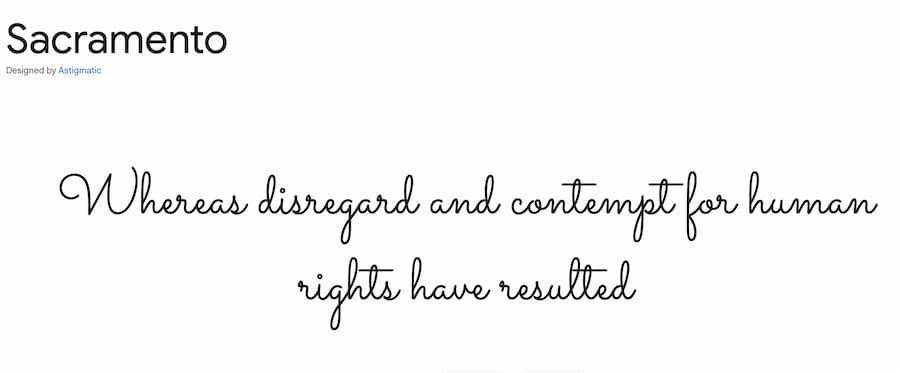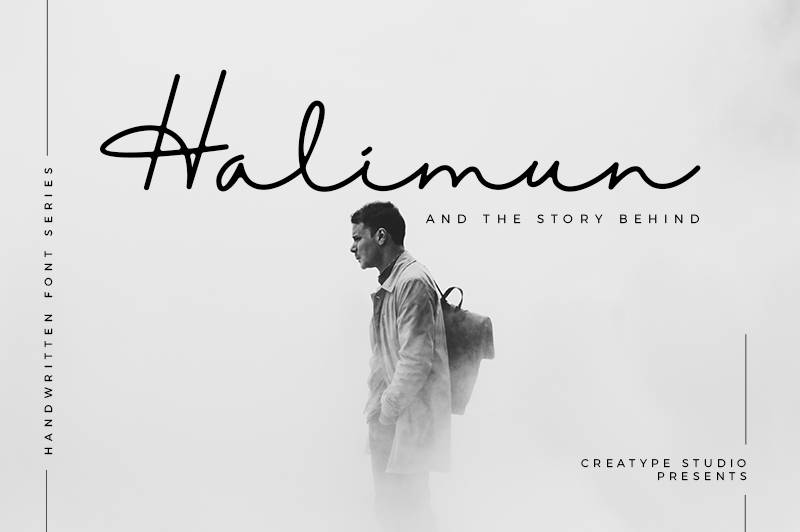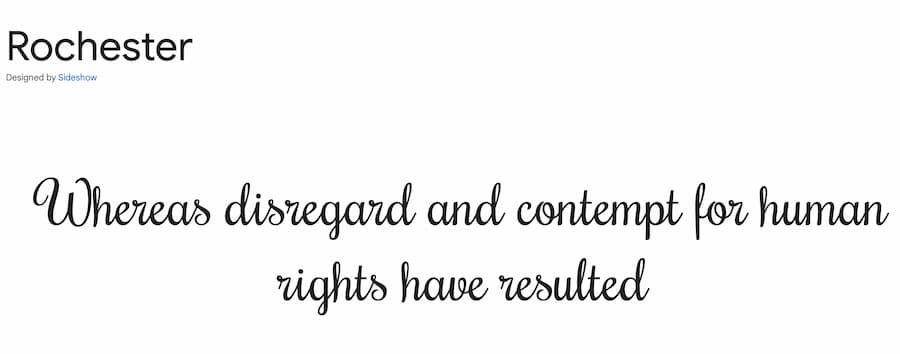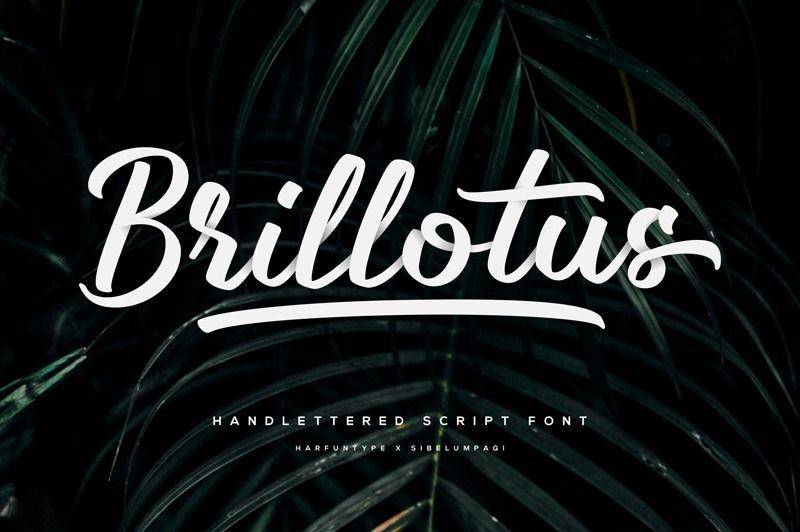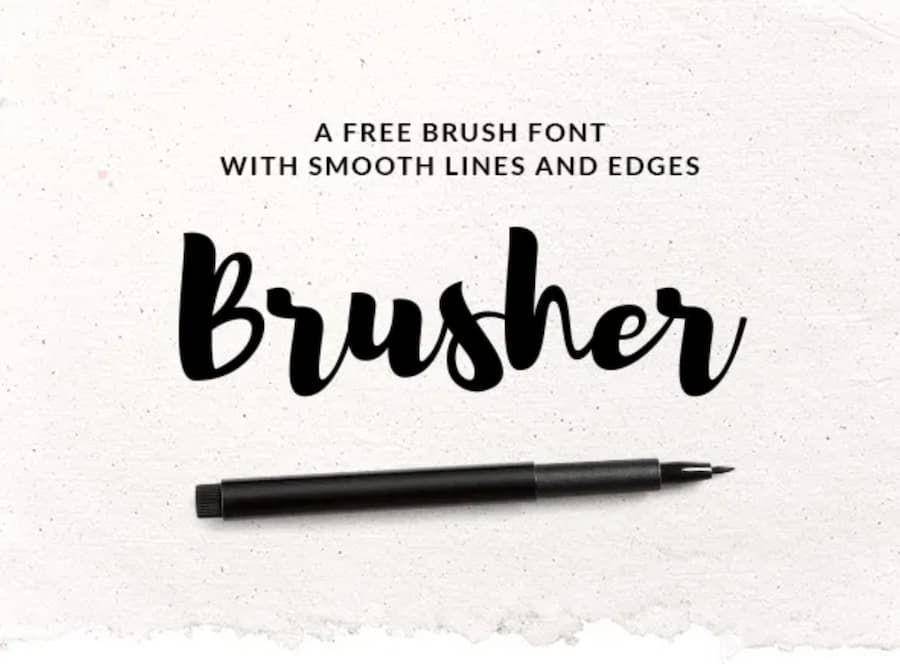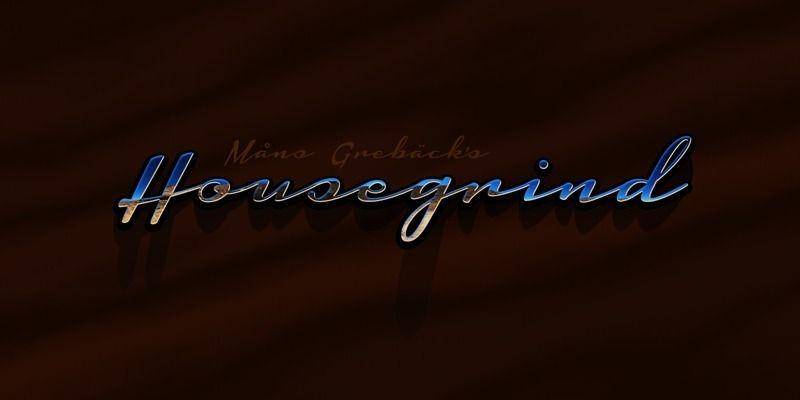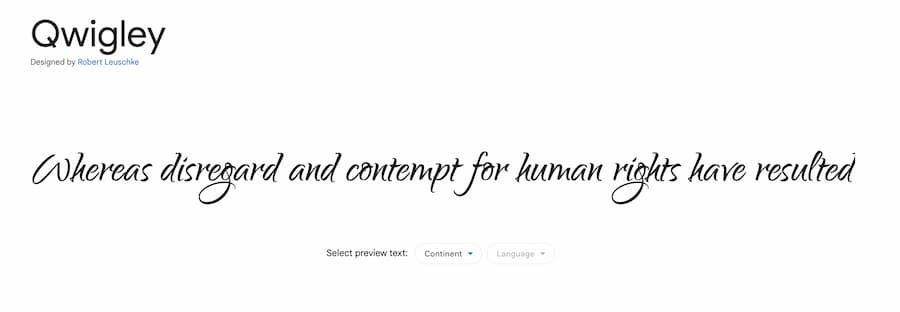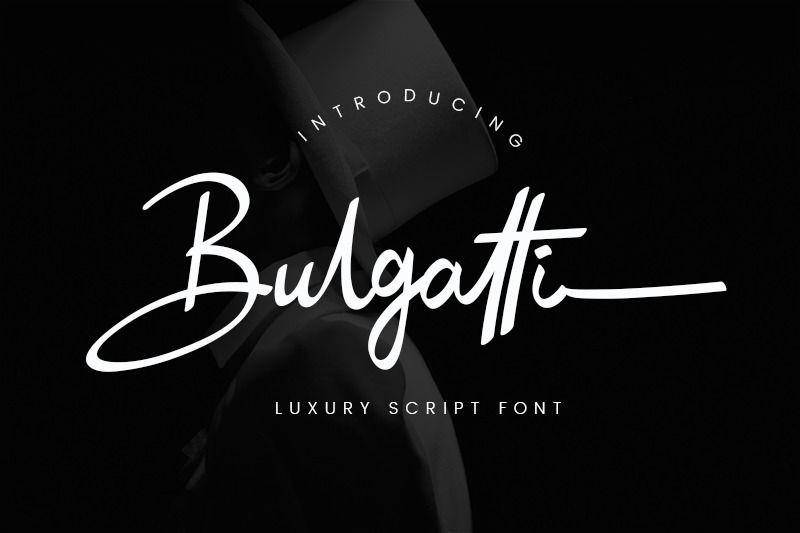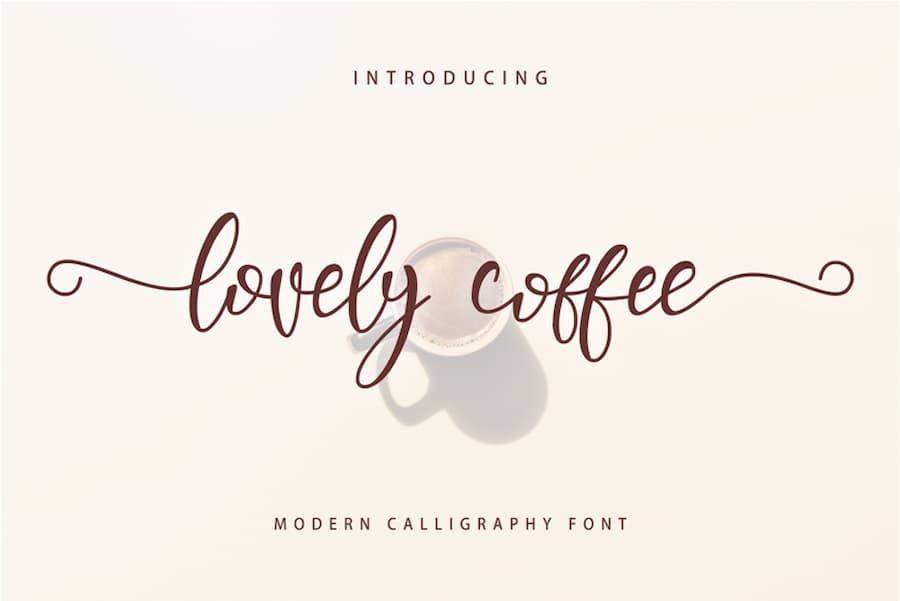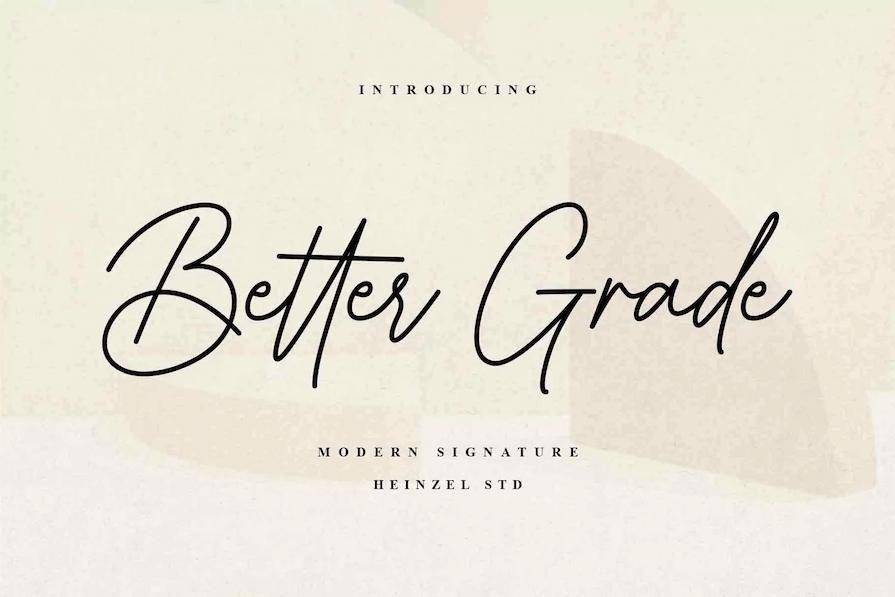
10 Font Tulisan Sambung Terbaik, Bikin Desain Makin Ciamik
Sebuah desain memerlukan banyak unsur untuk membuatnya memukau. Ada copywriting, ilustrasi, permainan warna, dan yang tidak kalah penting adalah fon atau font. Pemilihan bentuk huruf yang sesuai akan menambah sentuhan artistik plus mampu memainkan emosi pembaca.
Seperti font tulisan sambung terbaik di bawah ini. Cocok untuk digunakan sebagai logo, nama brand, hingga greeting. Meski bentuknya latin dan terhubung, penikmat desainmu tak akan kesulitan membacanya.
Font tulisan sambung terbaik
Penggunaan huruf  dalam desain disesuaikan dengan suasana yang ingin dibangun. Contohnya, font tulisan sambung yang cocok untuk acara informal, elegan, dan hangat. Kamu bisa menjumpai jenis huruf ini pada undangan pernikahan maupun papan welcoming.
Jenis font bersambung alias handwritten font sangat cocok diletakkan sebagai heading dalam desain, monogram, label brand, dan lain sebagainya. Yuk, pilih desain huruf yang paling cucok untuk desainmu!
1. Sacramento
ilustrasi font tulisan sambung terbaik (dok. google font)
Memulai listicle dengan tulisan khas tangan era jadul alias zaman dulu. Sacramento merupakan fon bersambung yang terinspirasi dari handwritten populer era 1950 sampai 1960-an. Tulisan ini saling terhubung, tegak, dan meliuk dengan jarak antar huruf cukup renggang sehingga mudah terbaca.
Dari tampilannya, Sacramento mungkin kurang cocok untuk dijadikan body font karena garisnya yang tipis. Namun, fon ini tetap memukau dan jelas terbaca ketika dijadikan header atau judul
2. Rochester
ilustrasi font tulisan sambung terbaik (dok. google font)
Membutuhkan font tulisan sambung terbaik yang cocok untuk mencuri atensi? Jika iya, bisa menggunakan Rochester. Fon ini merupakan jenis art deco yang ciamik untuk dijadikan header maupun penjelas dari keterangan utama.
Rochester memiliki garis tipis dengan untaian huruf layaknya tulisan tangan. Belum lagi huruf kapital yang berukuran jauh lebih besar dengan aksen tambahan. Hal tersebut  membuatnya kurang cocok untuk dijadikan body font karena akan terlihat cukup berantakan.
3. Brillotus
ilustrasi font tulisan sambung terbaik (dok. dafont)
Fon bersambung ala-ala coffee shop? Bisa lirik Brillotus. Untaian huruf tergambar ciamik dengan garis tebal, tetapi tetap jelas. Kreatornya menambahkan aksen menarik, yakni bayangan yang membuatnya terasa hidup. Gaya tulisan yang disajikan pun tegas, bersih, dan tetap dinamis.
Brillotus sendiri merupakan fon karya anak bangsa, lho! Fon ini dikembangkan oleh Sibelumpagi Studio. Versi demonya bahkan sudah menyediakan pengaturan fon untuk angka 1-9. Cus, beli, lalu unduh!
4. Brusher
ilustrasi font tulisan sambung terbaik (dok. befonts)
Kalau kamu tim bullet journaling versi digital seperti di tablet, maka wajib punya fon Brusher. Bentuknya yang rapi dengan variasi garis tebal dan lengkung tipis khas tulisan tangan. Tipe typeface cocok digunakan untuk berbagai kebutuhan, mulai dari judul, quote, bahkan masih cukup rapi untuk tulisan pendek.
Brusher masih sangat mudah terbaca meski termasuk huruf bersambung. Untungnya lagi, kamu bisa menggunakan fon ini untuk kepentingan pribadi maupun komersil secara gratis, tanpa perlu mencantumkan atribusi.
5. Housegrind
ilustrasi font tulisan sambung terbaik (dok. dafont)
Pertama kali melihat gambar, fon ini mengingatkan akan poster salah satu film Marvel. Meski bersambung dan mungil, Housegrind tetap mudah terbaca. Sebab, jarak antar hurufnya cukup jauh, pun ketebalan garisnya terasa tegas meski tetap memberikan sentuhan dinamis.
Housegrind font berbentuk italic alias miring ke kanan. Cocok digunakan sebagai keterangan judul utama ataupun pada sub-bagian. Font ini bisa kamu gunakan secara gratis untuk personal use only, ya!
6. Qwigley
ilustrasi font tulisan sambung terbaik (dok. google font)
Fon bersambung, tapi terpisah. Nah, gimana, tuh? Qwigley sejatinya menampilkan huruf terpisah yang termasuk jenis script. Fon ini memiliki ekor cukup panjang dan melengkung, serta letaknya cukup berdekatan. Dengan demikian, memberikan tampilan layaknya huruf sambung yang ciamik.
Pada contohnya, Qwigley cocok dijadikan sebagai judul. Kelebihan lainnya adalah, fon ini juga cukup menarik dijadikan body font. Kalau kamu ingin menghadirkan desain old school atau vintage, maka Qwigley bisa digunakan pada narasi.
7. Bulgatti
ilustrasi font tulisan sambung terbaik (dok. dafont)
Bulgatti memberikan kesan mahal dan elegan pada siapa saja yang membaca tulisan dengan fon ini. Bentuknya bersambung dengan aksen pada huruf tertentu. Fon ini mirip tulisan tangan yang menggunakan spidol dengan permukaan memanjang alih-alih bulat.
Hurufnya yang tidak sejajar juga membuatnya semakin mirip dengan tulisan tangan ala-ala cerita CEO di Wattpad. Fon handwritten ini menyediakan variasi huruf kapital dan kecil, serta simbol khusus.
8. Lovely Coffee
ilustrasi font tulisan sambung terbaik (dok. dafont)
Fon tulisan sambung terbaik nyaris selalu identik dengan gaya kaligrafi. Salah satunya si Lovely Coffee ini. Dengan huruf tipis dan berdekatan, terdapat lekukan yang saling menghubungkan antara satu huruf dengan lainnya. Aksen di awal dan akhir huruf pun bisa ditambahkan untuk fungsi dekoratif.
Ada 248 karakter yang bisa digunakan setelah mengunduhnya. Kamu bisa menghias desain dengan huruf kapital, huruf kecil, dan simbol-simbol.
9. Better Grade
ilustrasi font tulisan sambung terbaik (dok. fontbundles)
Logo brand ala signature sedang banyak digemari oleh pemilik usaha. Kalau kamu juga ingin membuatnya, bisa menggunakan fon Better Grade ini. Hurufnya ditampilkan tipis dan membulat di ujung membulat yang terkesan simple dan clean
Menggunakan fon ini sebagai logo ataupun judul sebuah desain menampilkan visual yang elegan. Permainan bentuk yang variatif seperti menambahkan panjang tangkai huruf, lengkungan, hingga sambungan membuatnya mudah terbaca.
10. Halimun
ilustrasi font tulisan sambung terbaik (dok. dafont)
Jika ingin menampilkan desain dengan kesan dramatis, Halimun cocok dipakai. Fon ini memiliki jarak antar huruf yang cukup jauh dan memanjang. Tidak banyak aksen yang disematkan. Adapun kreatornya membuat huruf membulat yang terhubung satu sama lain.
Sangat cocok untuk dijadikan judul sebuah poster atau undangan pernikahan. Kesannya elegannya dapat, intimate-nya pun terasa saat membacanya.